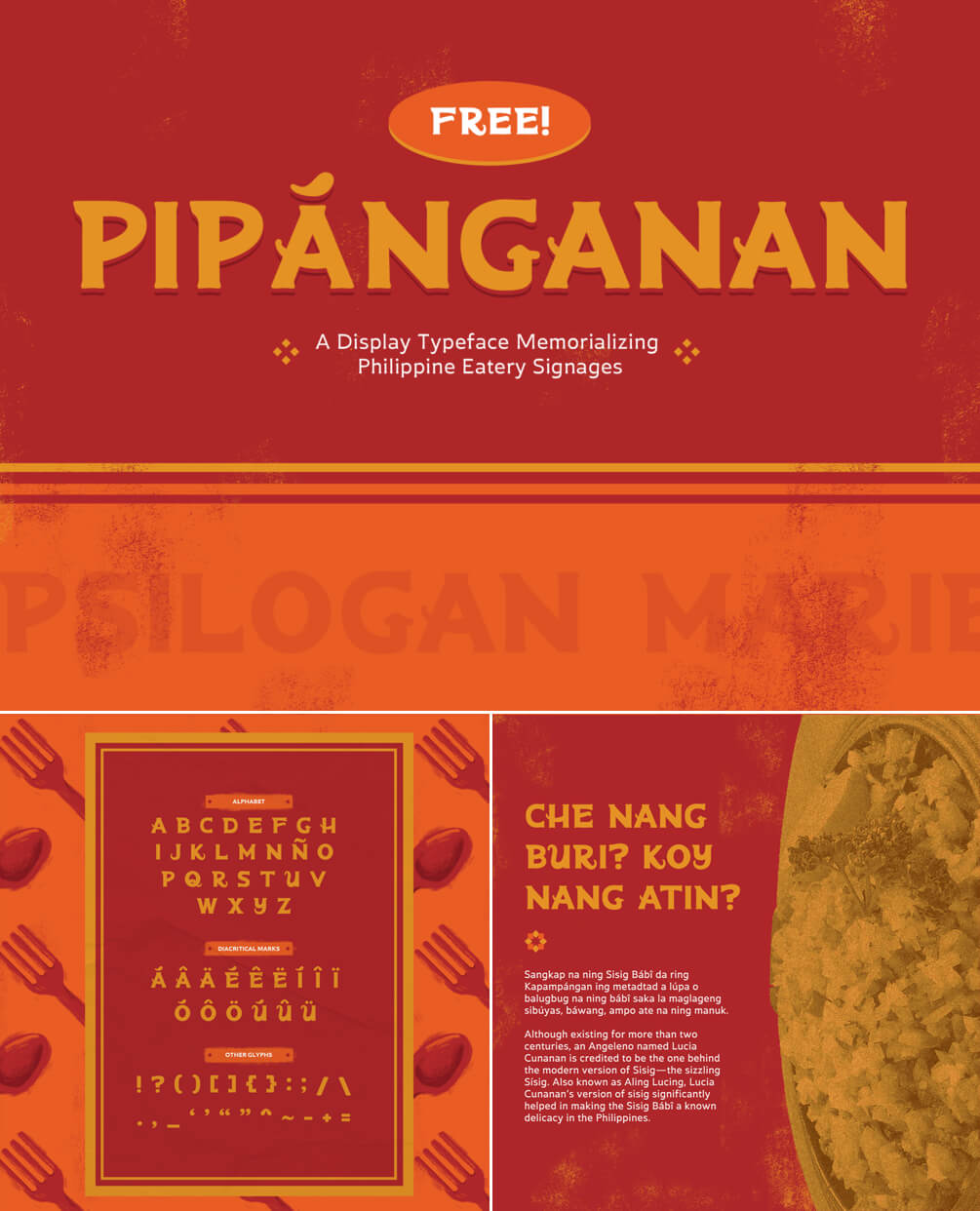
Pipánganan
Wer beim Anblick dieses Fonts automatisch Appetit verspürt … »Pipánganan« soll an die Beschilderung von philippinischen »Carinderias« erinnern. Der Free Font steht ab sofort zum Downloaden bereit.
Pipánganan Free Font
Die »Carinderias« gehören zu gastronomischen Betrieben, die auf den Philippinen besonders von der Corona-Pandemie betroffen sind. Der Designer und Illustrator Cid Gonzales möchte mit dem Font sprichwörtlich Zeichen setzen und eine Schrift an die Hand geben, die authentisch das einstige Flair dieser Eßlokale einfängt.